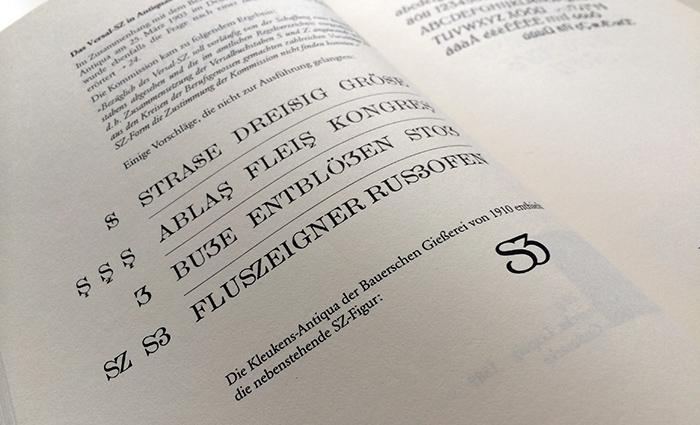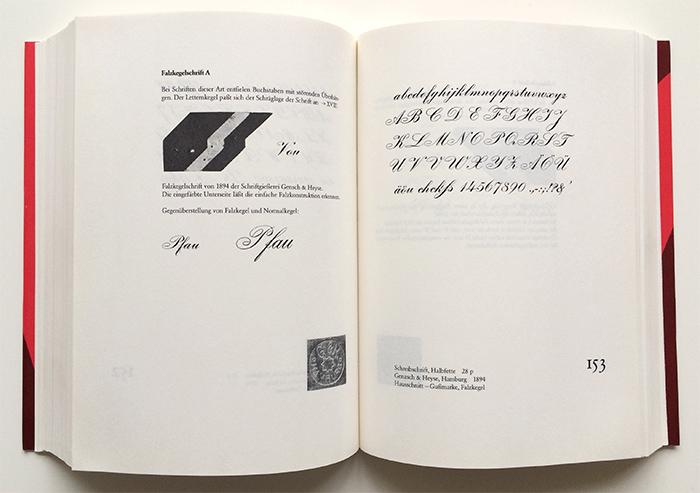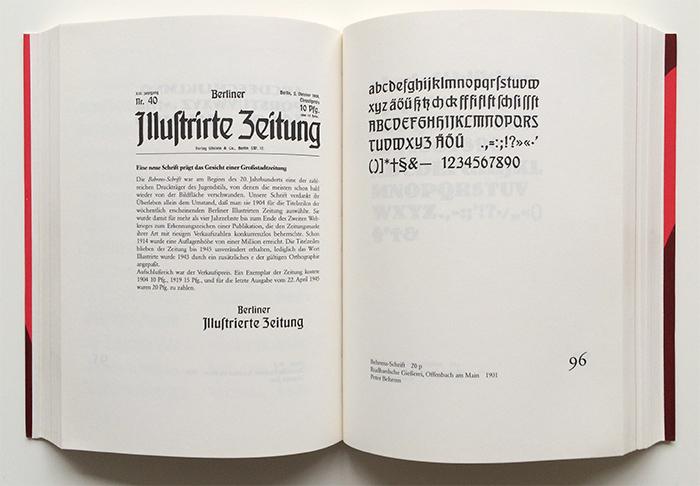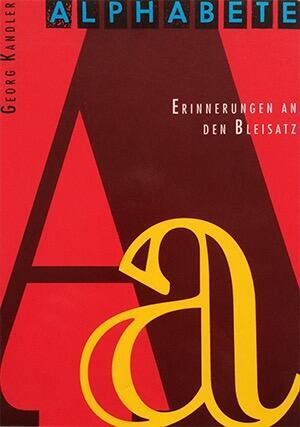
Alphabete: Erinnerungen an den Bleisatz I
Georg Kandler (1913–2004) war gelernter Schriftsetzer und konnte über Jahrzehnte hinweg die einschneidenden Veränderungen dieses Berufes von wechselnden Standorten und Positionen aus mitverfolgen. Nach Ende des Zweiten Weltkrieges erhielt er in einer britischen Druckerei am Suez-Kanal Einblick in die Eigenarten englischer Satztechnik und fand Zugang zur entsprechenden Fachliteratur. Anfang der 1950er-Jahre legte er die Schriftsetzer-Lehrmeisterprüfung ab und war anschließend mehr als zwanzig Jahre Berufsschulleiter für grafische Fachklassen in Braunschweig.
Fast hautnah erlebte er er den Übergang vom Bleisatz zu den neuen Verfahren der Satzherstellung und wurde Zeuge, wie bewährte Druckschriften zusammengeschüttet ins Altmetall wanderten. In dieser Zeit setzen seine Bemühungen ein, seltene Schriften sicherzustellen und zusammenzutragen.
Außerdem sammelte er auch Material zu typografischen Themen, die in Fachzeitschriften auftauchten, zum Beispiel zu Gussmarken, zum Falzkegel, dem Musterschutzgesetz oder der Einführung von (Antiqua-)ß und ẞ.
Im zweibändigen Werk »Alphabete – Erinnerungen an den Bleisatz« werden Bleisatzschriften aus 29 europäischen Schriftgießereien dargestellt. Einige davon entstanden vor mehr als 100 Jahren und konnten vom Autor im letzten Augenblick vor der Vernichtung bewahrt werden. Angereichert ist das Werk darüber hinaus mit vielen kurzen Fachbeiträgen zu typografischen Themen.
Inhalt:
• Die Schriftgießereien
• Klassifikation der Schriften
• Die Schriftfamilie
• Die Schriftgarnitur
• Gußmarken
• Der Falzkegel
• Vom typographischen System
• Druckersprache und Synonyme
• Die Alphabete, Hinweise
• Die Buchdruckletter
• Ligaturen – heute und gestern
• Seltene Ligaturen
• Das Qu in den Schriften der Renaissance-Antiqua
• Kapitälchen
• Das Antiqua-ß
• S & G und der amerikanische Schriftguß
• Ungewöhnliche Ausnutzung des Letternkegels
• Akzente im Setzkasten
• Überhänge und Unterschneidungen
• Das Versal-SZ in Antiqua-Schriften
• et-Zeichen
• Monotype-Schriften
• Gleicher Schriftgrad – verschiedene Systeme
• Schreibmaschinenschriften
• Erkennungsmerkmale bei Groteskschriften
• Von Spießen und Blockaden
• Futura – die neue Groteskschrift
• Groteskschriften im Zeilenguß
• Futura – Gerangel um die endgültige Buchstabenform
• Steile Futura
• Die Gill-Grotesk
• Iller oder Dreier?
• Eine neue Schrift prägt das Gesicht einer Großstadtzeitung
• Helios, die Schrift mit zwei Gußmarken
• Schriften für den Anzeigensatz
• Frauen stellen sich zum Wettsetzen
• 219 x Buchstabe »G«
• Die turmino-Fächer im Setzkasten
• Übersetzer
• Englische Schreibschriften
• Falzkegelschrift A
• Die Schriftsperrklötzchen von Schelter & Giesecke
• Umlautversalien bei deutschen Schriftgießereien
• Die Mistral mit zusätzlichen Bestimmungshilfen
• Mit der Prägefest Vorstoß in die Werbung
• Salto – 20 p auf Doppelmittelkegel?
• Die Buchstaben in den ersten Frühdrucken
• Das Musterschutzgesetz von 1867
• Die Münster-Gotisch: keine Gotisch!
• u und n in Frakturschriften
• Brotschriften und Entlohnung
• Vom et-Zeichen zum »und so weiter«
• Das runde r
• Wohin mit den Pünktchen?
• Die Signatur als Erkennungszeichen
• Vom Alineazeichen zum Satzeinzug
• W. Pfnor, Großherzogl. Hofkammersekretär und Schriftgießer
• Sonderlinge ch und ck
• Gekrönte Häupter am Setzkasten